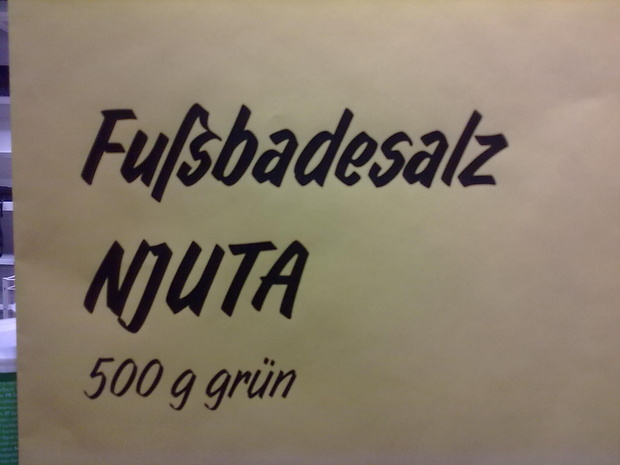
Ein Déjà-vu
Au, bertel stimmt! Du bist aber auch wirklich leidgeprüft hier im Forum. Erst der Binde-Strich, dann der Bertel – und »Weiß« sogar doppelt. Zum Glück kann das einen Jahresweißen nicht erschüttern, oder? attachment.php?attachmentid=1357
Mühsam. Eine gemischte Schreibweise wäre hübscher gewesen und könnte dennoch sehr eigenständig gestaltet werden.
Weiter unten auf dem Etikett steht auch noch »KESSLER«. Unterschiedliche Schreibweisen hätte ich auf alle Fälle innerhalb eines Etikettes vermieden.
Für mich sieht der so aus, als hätte der Gestalter das Esszett-in-Namen-Problem zu lösen versucht, ohne ein ẞ zur Hand zu haben. Wenn die Annahme zutrifft, finde ich das Ergebnis sehr gelungen. Besser kann man wohl kaum einen Kleinbuchstaben in eine Gruppe großer hinein schummeln. Oder?
Ziemlich geschickt aus der Affaire gezogen.
Eine gemischte Schreibweise wäre hübscher gewesen und könnte dennoch sehr eigenständig gestaltet werden.
Womöglich habe ich hier ein Terminologieproblem: Inwieweit ist KEßLER nicht gemischt? :-?
Das ist kein gemischter Satz, sondern Versalsatz mit einem Fehler drin. :tutor:
Weiter unten auf dem Etikett steht auch noch »KESSLER«. Unterschiedliche Schreibweisen hätte ich auf alle Fälle innerhalb eines Etikettes vermieden.
Dafür hätte ich ausnahmsweise sogar Verständnis, das eine soll ein Logo sein, das andere ist Text. Wobei das Logo als solches nicht erkennbar ist … aber erstaunlich, welche Druckqualität auf einem Kassenbon machbar ist :-P
eine Handbreit Schnee unter den Serifen. :-D
Ich guck nur mal schnell aus meinem Stapel klausurrelevanter Lektüre hervor, weil ich da grad auf der Suche nach etwas wichtigem im Ordner "Kram" was anderes hübsches wieder gefunden habe:
Aufgenommen bei meinem berühmten schwedischen Inneneinrichter ;)
oh schön, weiß jemand wie der Font heißt?
Am Sonnabend bin ich zur Beobachtung der Neujahrsfeierlichkeiten mal mit dem Fotoapparat durch New Yorks Chinatown geschlendert (und auf dem Heimweg noch ein bisschen durch Soho) und habe bei der Gelegenheit gleich noch ein paar (hoffentlich) typographisch relevante Fundstücke aufgenommen. Ich habe noch nicht alle Bilder webgerecht aufbereitet, deshalb aus aktuellem Anlass gibt’s erst mal ein paar Schaufensterwerbungen zum Valentinstag. (Alle Bilder sind anklickbar; die Links führen zu größeren Versionen.)
Falls es nicht offensichtlich sein sollte: die beworbenen Geschäfte verkaufen Speisen französischer Art, Damenbekleidung und -schuhe, Fitnesskleidung und -zubehör, Turnschuhe und noch mal Damenbekleidung.
Die Reporter zum Valentine‘s Day hätte ich ja auch nie gewagt ...
... aber fast besser als selbstgemalt :-(
Neulich mit dem Handy im Forum …
Woher tapatalk das wohl weiß … ;-)
Guten Abend,
da ich keinen wirklich passenden Thread gefunden habe, möchte ich mich hier darüber Lustig machen, das nicht nur Inhaber von „Willi’s Würstchenbuden“ oder dubiosen Läden, die „Musik-CD’s“ verkaufen, keine Ahnung vom Deppenapostroph haben sondern auch die Herren Designer einer Kampagne einer großen Elektronik-Handelskette
:lol:
Finde ich irgendwie traurig … zumal es nicht mal konsequent auch bei Tablet’s und Notebook’s verwendet wird. Oder gilt hier das ungeschriebene Gesetzt, dass Akronyme/Abkürzungen ihr Plural-s mit Apostroph bekommen? Schreiben wir also bald auch „Ein LASER, zwei LASER’s“? :neenee:
Mal ganz davon abgesehen, dass der richtige Apostroph fehlt …
Ich finde einen (Deppen-)Apostroph an der Stelle recht hilfreich. Er erleichtert meines Erachtens die Lesbarkeit des Wortes ungemein. Das Ganze ist sicherlich auch der Versalschreibweise geschuldet; PCs wäre die elegantere Lösung gewesen.